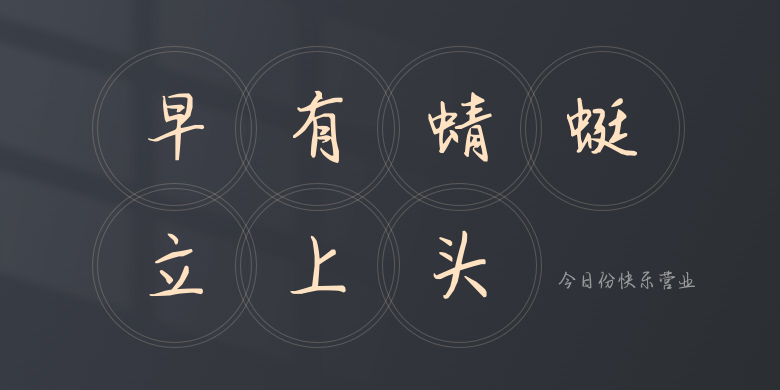
今日份快乐营业,这款字体结构工整、笔画清晰,兼顾美观与易读性,适用于标题、正文、海报、包装、LOGO 等多种场景。字形优雅稳定,风格百搭耐看,适配日常排版与创意设计,让文字呈现更舒适、更具质感。今日份快乐营业一笔一画,皆是细节,以均衡的比例、流畅的线条打造舒适视觉体验,字形端正大气,风格简约现代。无论是商业设计、品牌宣传还是日常排版,都能轻松驾驭,让文字更有格调与力量。今日份快乐营业字体下载。